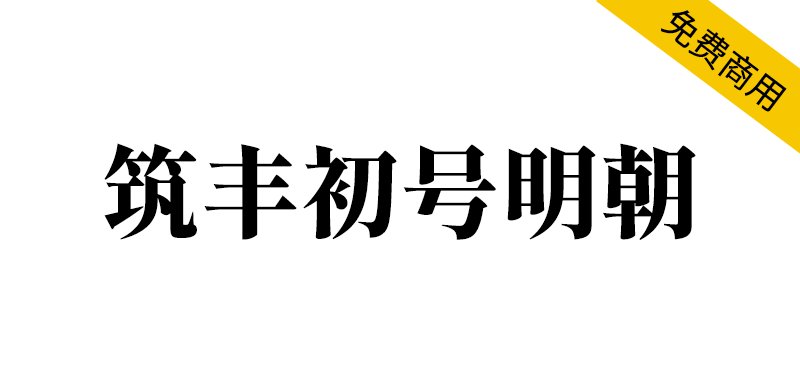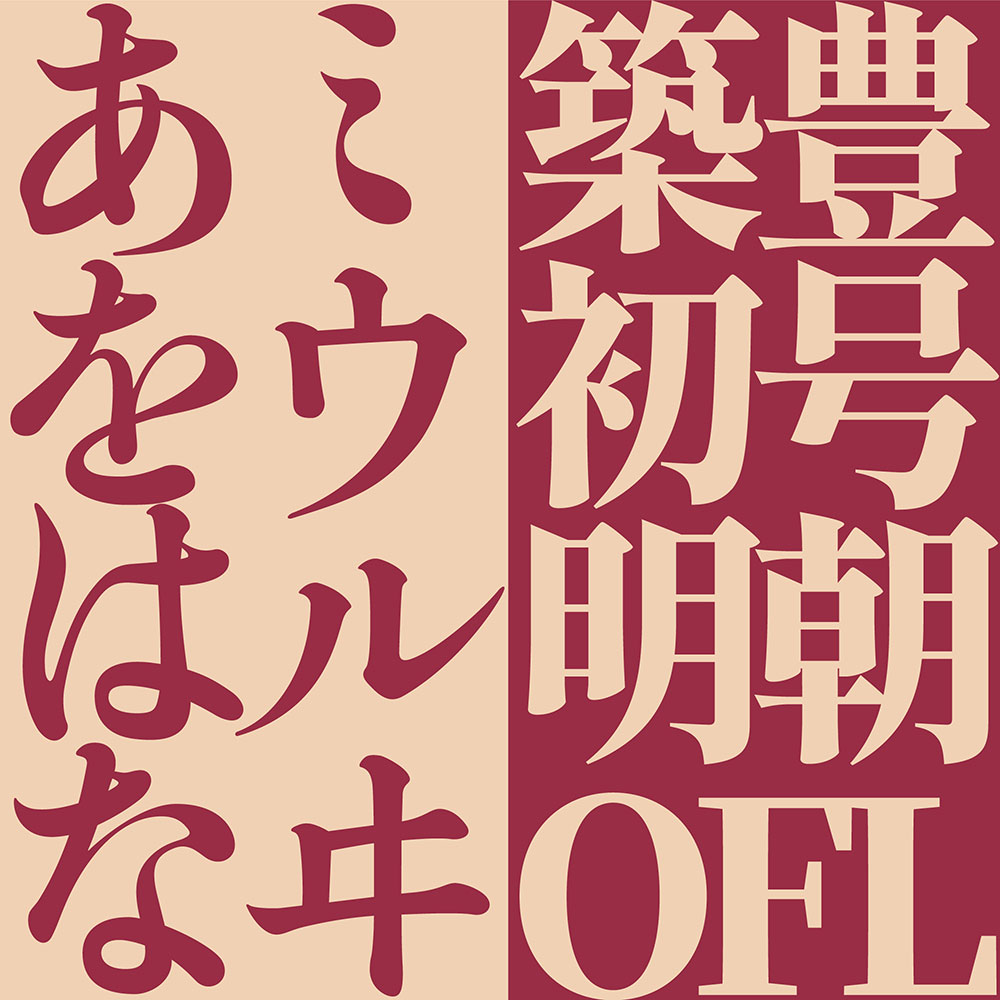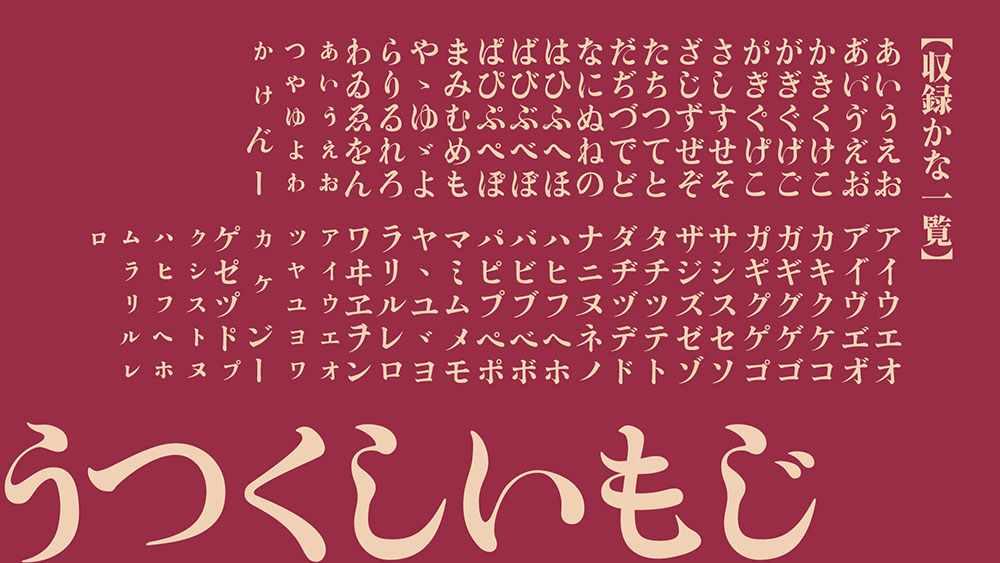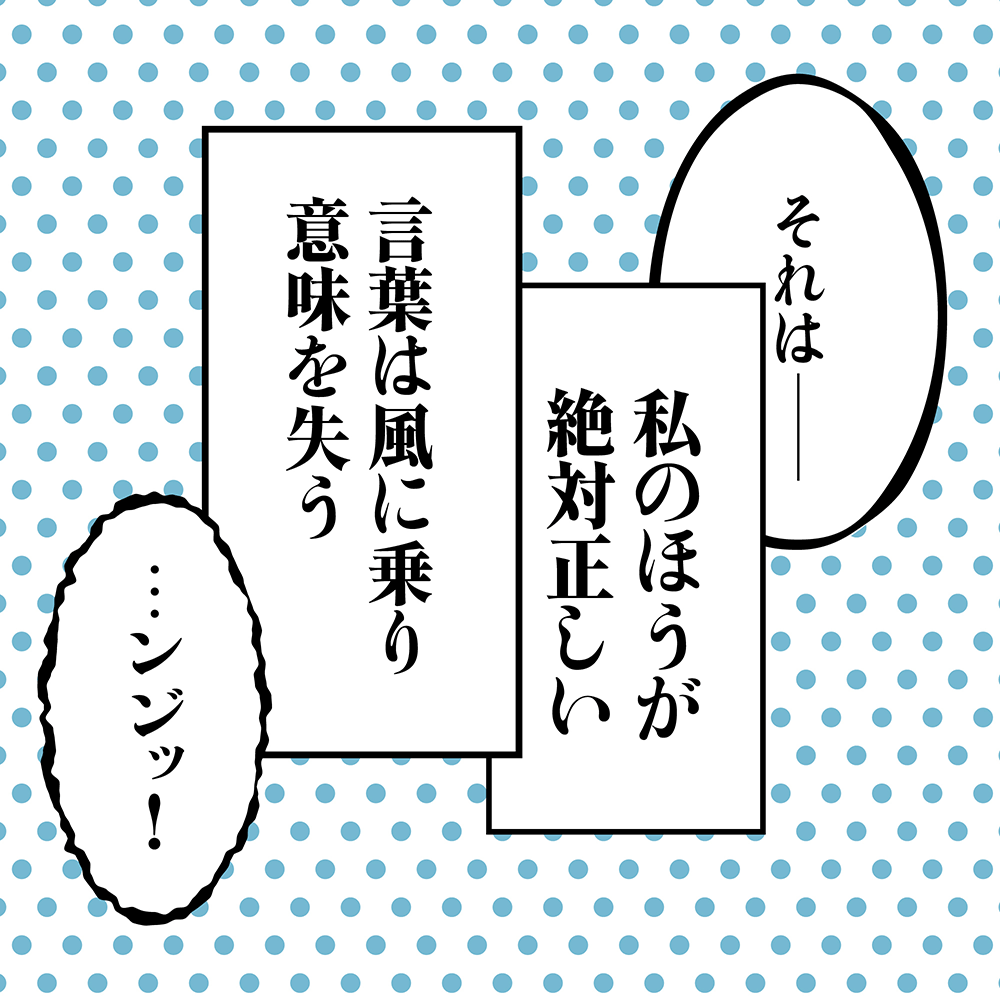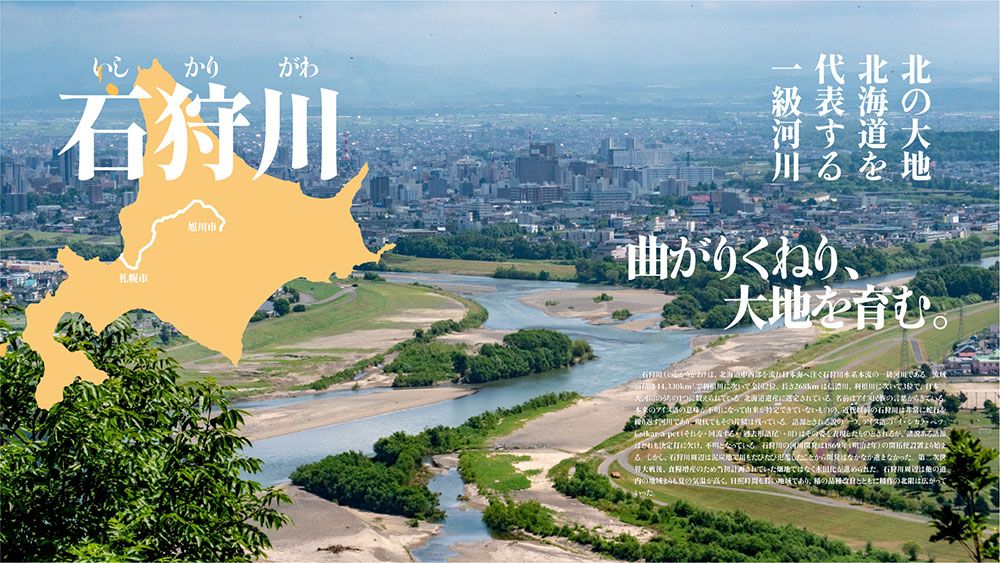
【筑丰初号明朝】适用于标题的复古风格宋体字体
想为你的设计注入复古灵魂?筑丰初号明朝这款融合传统与现代的标题字体,将带给你意想不到的视觉冲击。它巧妙结合了传承百年的筑地初号假名字形与锐化处理的源流明体汉字,既有古典字体的筋骨笔触,又不失现代设计的清晰锐利。更令人惊喜的是,这款精心打磨的字体完全免费商用,个人和企业都能无门槛使用。无论是打造品牌标识还是设计海报标题,它都能让你的作品瞬间提升质感。
筑丰初号明朝(築豊初号明朝)是一款适用于标题等需突出显示部位的复古风格明朝体。其假名部分基于传承筑地初号传统的「筑丰初号标题假名」优化而成,兼具浑厚骨感与鲜明笔触特征。汉字部分则采用经过锐化处理的思源宋体衍生字体「源流明体2.100」。特此向原始字体开发者致以深切谢意。收录字符:平假名、片假名、汉字、部分符号与标点、西文(英文)。
見出しやタイトルなど目立たせたいところに向いたオールドスタイルの明朝体です。伝統的な築地初号の流れを汲む、「築豊初号見出しかな」を元にブラッシュアップされた仮名とどっしりとした骨のある筆脈が特徴です。漢字には角立て処理の施されている源ノ明朝の派生フォント「源流明朝2.100」を利用しています。オリジナルのフォントに深く感謝いたします。収録文字、ひらがな、カタカナ、漢字、一部記号・役物、欧文(英語)